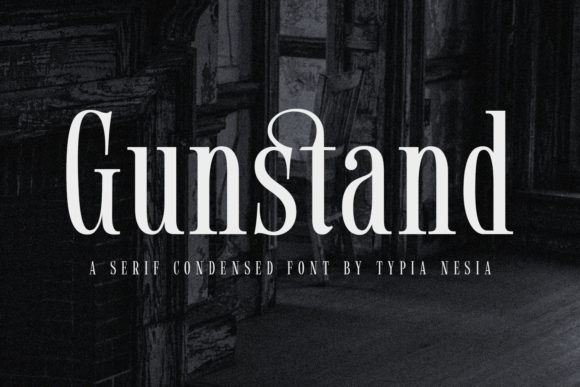
Creativefabrica Gunstand Font
[Creativefabrica] Gunstand Font
Оружейная стойка - это современный шрифт с засечкой.
Этот шрифт будет выглядеть превосходно в любом контексте, независимо от того, используется ли он на оживленном фоне или как самостоятельный заголовок!